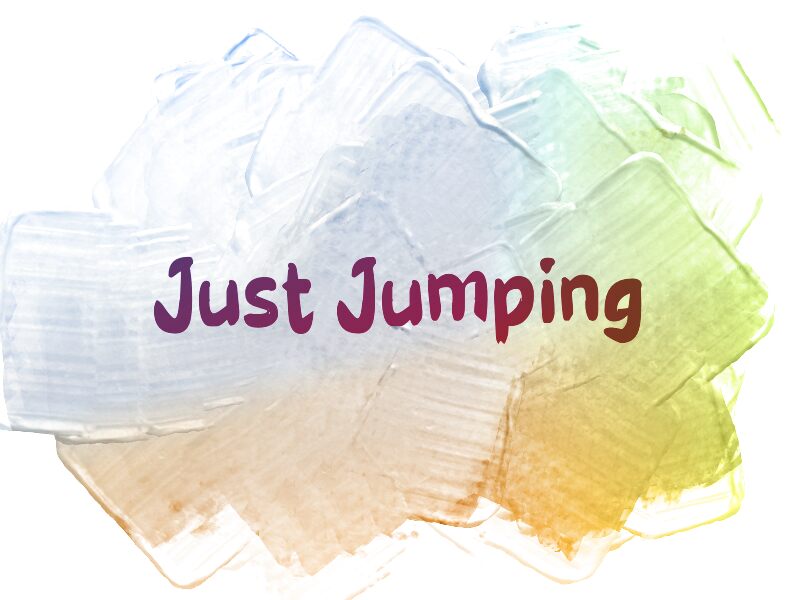
Just Jumping par Wep est une police brush script gratuite, ludique et pleine de vie, au rythme spontané et peint à la main. Les lettres sont douces et rebondissantes, avec des traits épais et arrondis, des courbes fluides et des formes verticales pleines d'entrain qui donnent l'impression que le texte a été posé là en un bond plutôt que composé soigneusement.
Ce dynamisme en fait un choix tout naturel pour le packaging d'articles pour enfants, les invitations, l'identité visuelle de cafés chaleureux, les titres de scrapbooking ou les bannières de réseaux sociaux nécessitant une touche manuscrite amicale. En tant que police gratuite, elle est parfaite pour les affichages courts, des titres d'affiches aux autocollants, car l'énergie irrégulière du pinceau apporte une note décontractée et solaire à n'importe quel mot.
Just Jumping